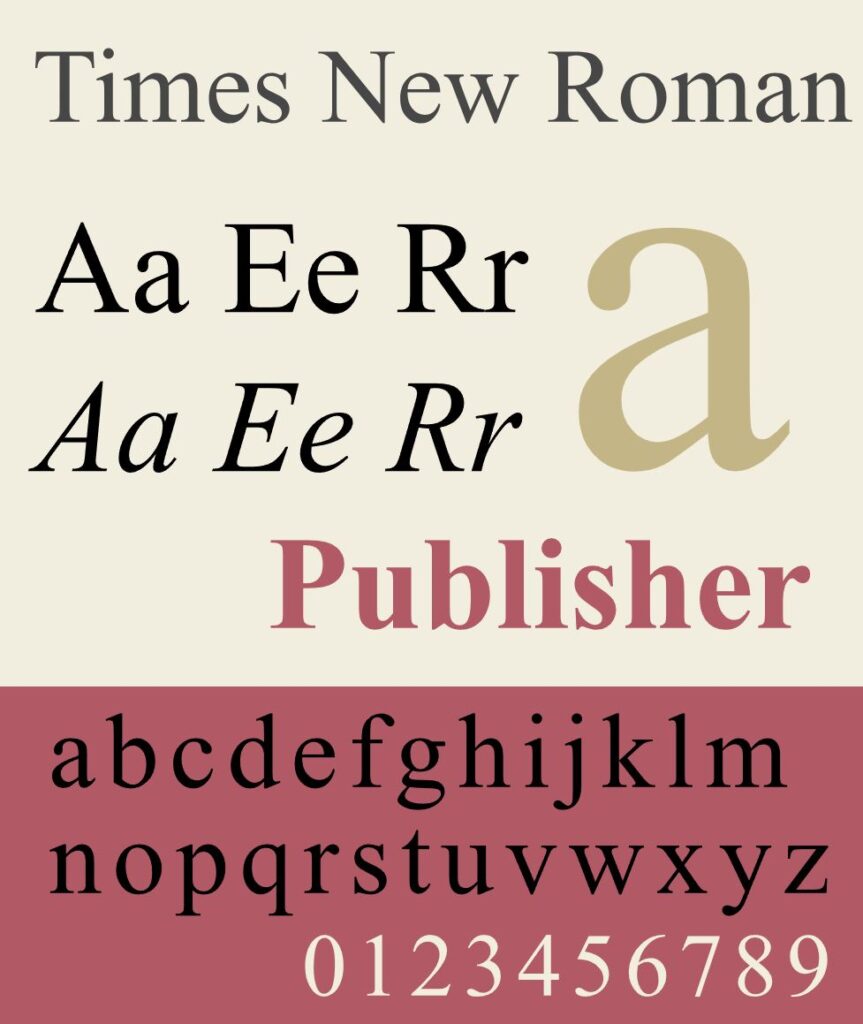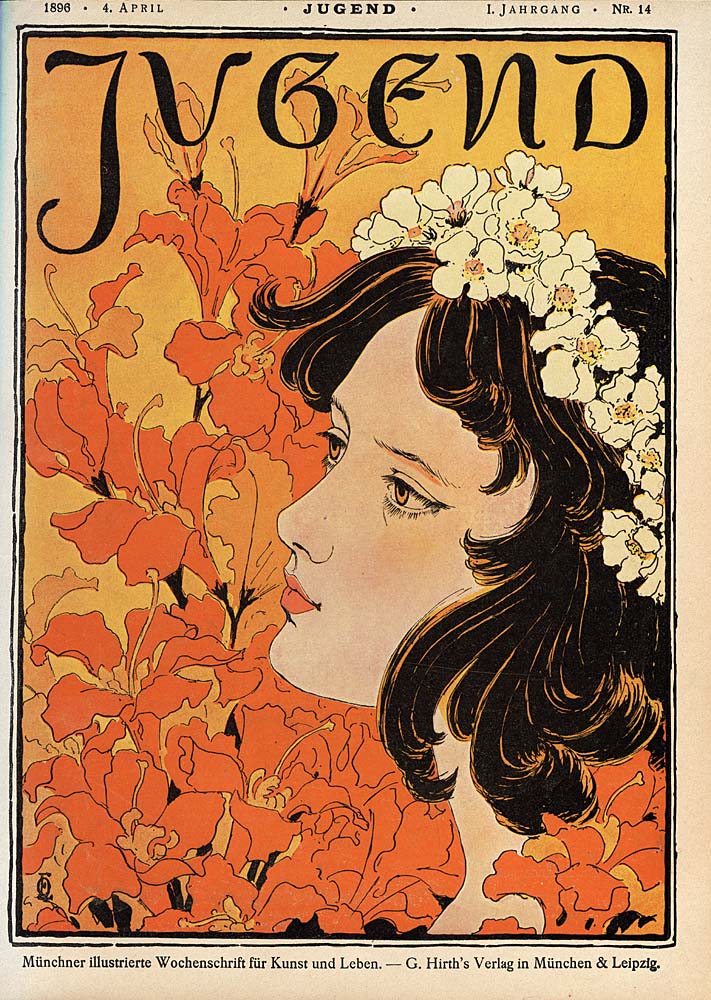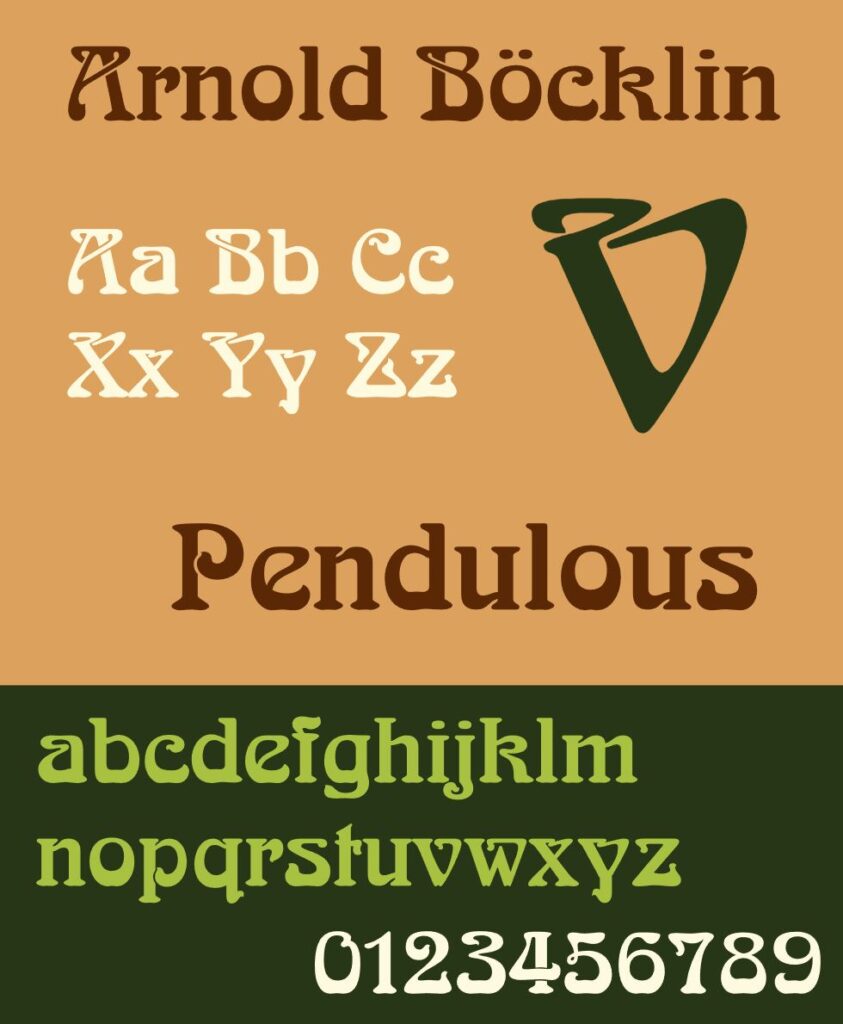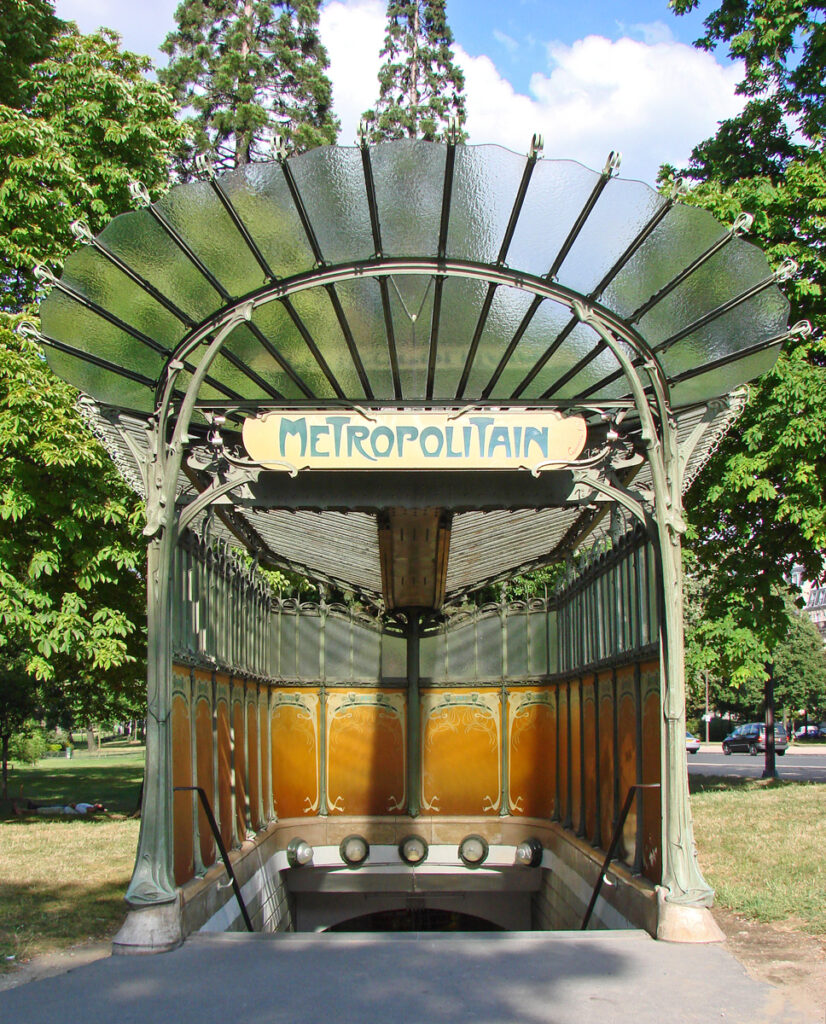
19. Jh. – Jugendstil und serifenlose Schriften
1880 und der Jugendstil
Gegen Ende des 19. Jahrhunderts erreichte der Jugendstil seine Blüte, die bis ins frühe 20. Jahrhundert anhielt. Der Begriff stammt von der Münchner Zeitschrift Die Jugend, die Wurzeln der Bewegung liegen jedoch in England. Dort gilt William Morris als Begründer, der gotische und barocke Elemente mit japanischen und orientalischen Einflüssen verband.
Der Jugendstil erfasste nahezu alle Kunstgattungen und entstand als Protest gegen Vereinheitlichung und Normierung. Typisch sind geschwungene, pflanzenhafte Linien, inspiriert von der Natur. Diese Formensprache spiegelt sich auch in den Schriften wider: kräftig, geschwungen und stark variierend in der Linienstärke. Berühmte Beispiele sind die Eckmann von Otto Eckmann (1865–1902), dessen Leitmotiv der Schwan zum Symbol des Jugendstils wurde, sowie die Arnold Böcklin des Schweizer Künstlers gleichen Namens.
1900, die Times und die serifenlosen Schriften
Jede Stilrichtung ruft eine Gegenbewegung hervor. Nach der Strenge des Klassizismus und dem verspielten Jugendstil wandte man sich im frühen 20. Jahrhundert wieder typografisch klaren, anspruchsvollen Arbeiten zu. Klassiker wie Baskerville, Bodoni und Bembo wurden neu entdeckt und überarbeitet.
Die bedeutendste Neuschöpfung dieser Zeit war die Times, entwickelt von Stanley Morison im Auftrag der Londoner Zeitung The Times. 1932 erschien die erste Ausgabe mit der neuen, bis heute einflussreichen Barock-Antiqua.
Parallel hielten die serifenlosen Schriften Einzug. Als Geburtsjahr gilt 1898 mit der Akzidenz-Grotesk, hervorgegangen aus Vorläufern wie der Royal-Grotesk von Ferdinand Theinhardt. Herausgegeben von der Berliner Schriftgießerei Berthold, wurde sie zur Wegbereiterin zahlreicher späterer Klassiker, darunter Helvetica und Univers.